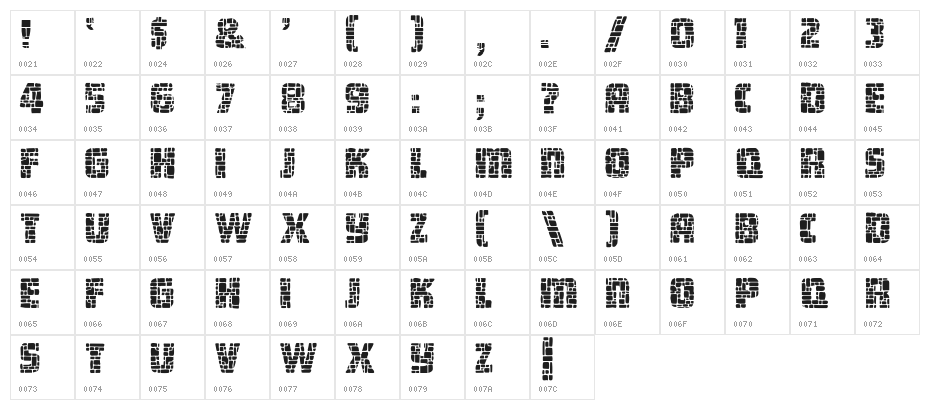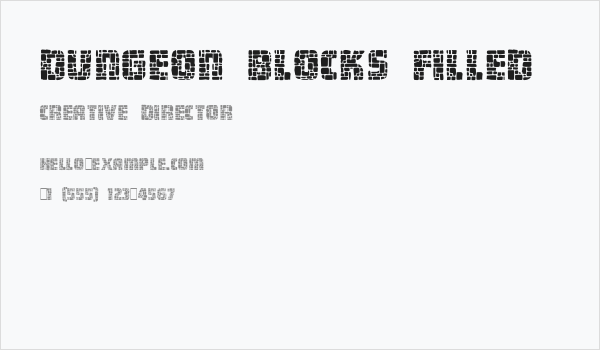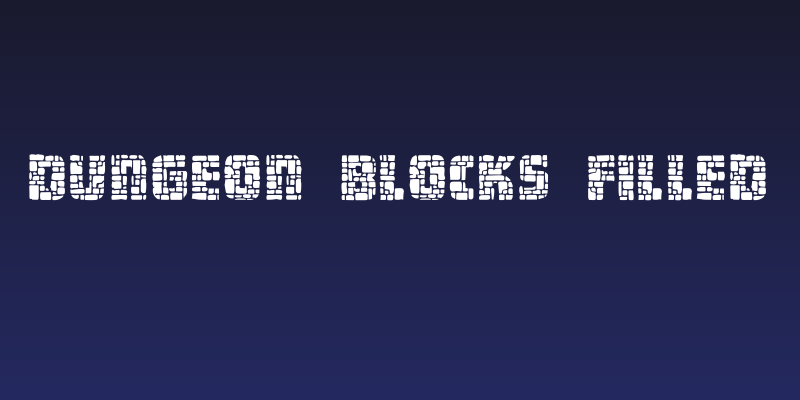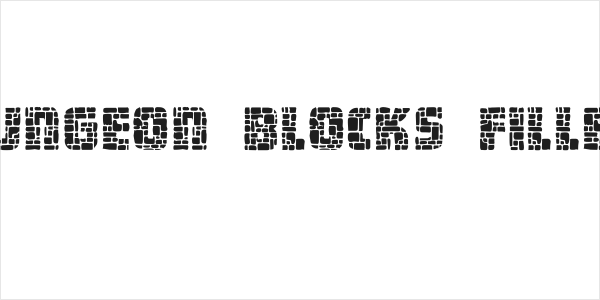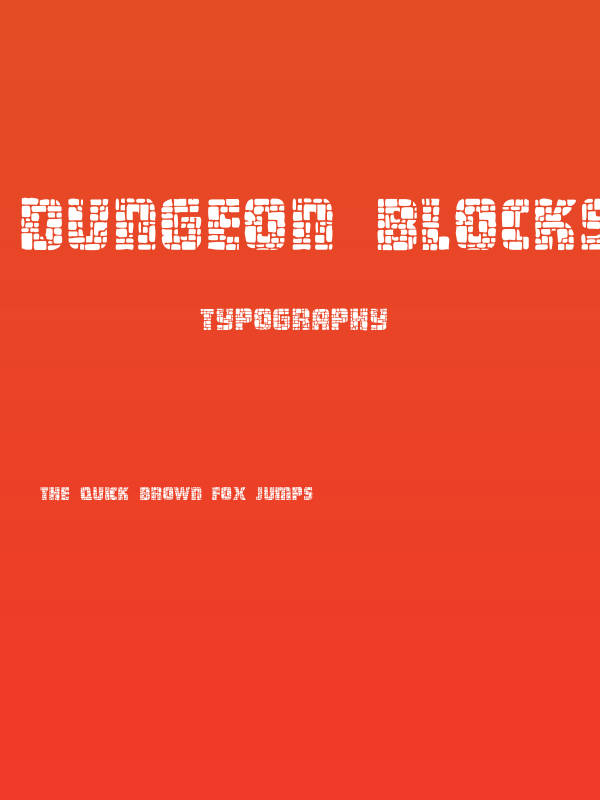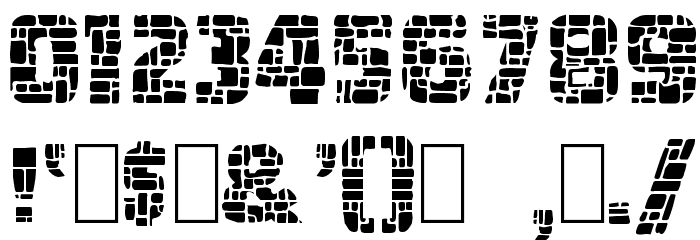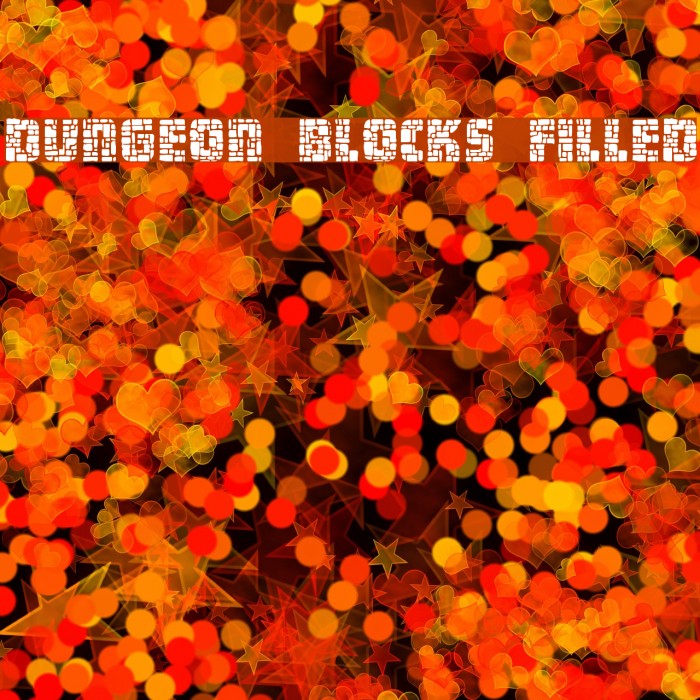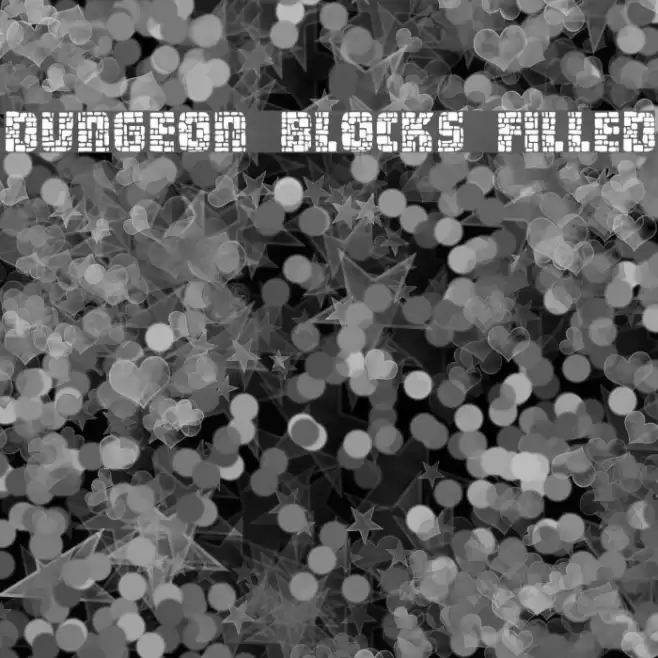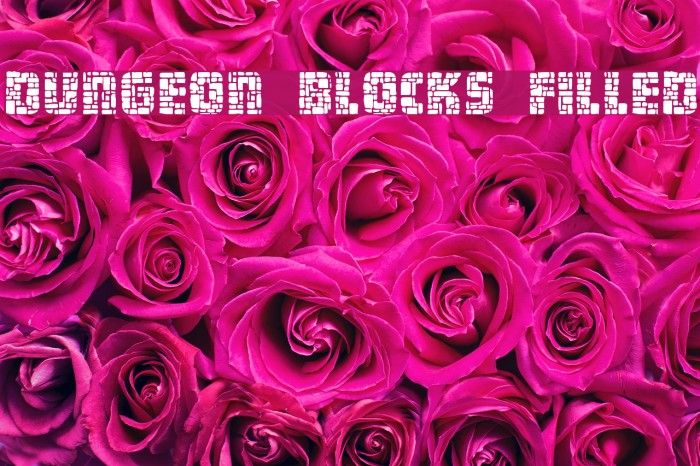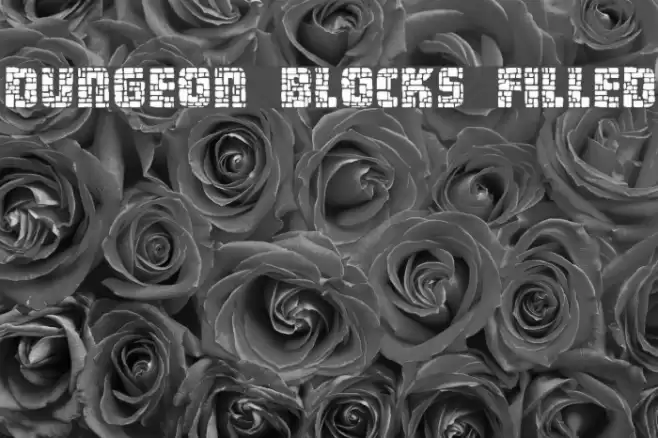
Dungeon Blocks Filled Font
| Рекомендуемые проекты | Ideal for game titles, posters, themed events, escape room branding, or any project needing a strong, adventurous aesthetic. |